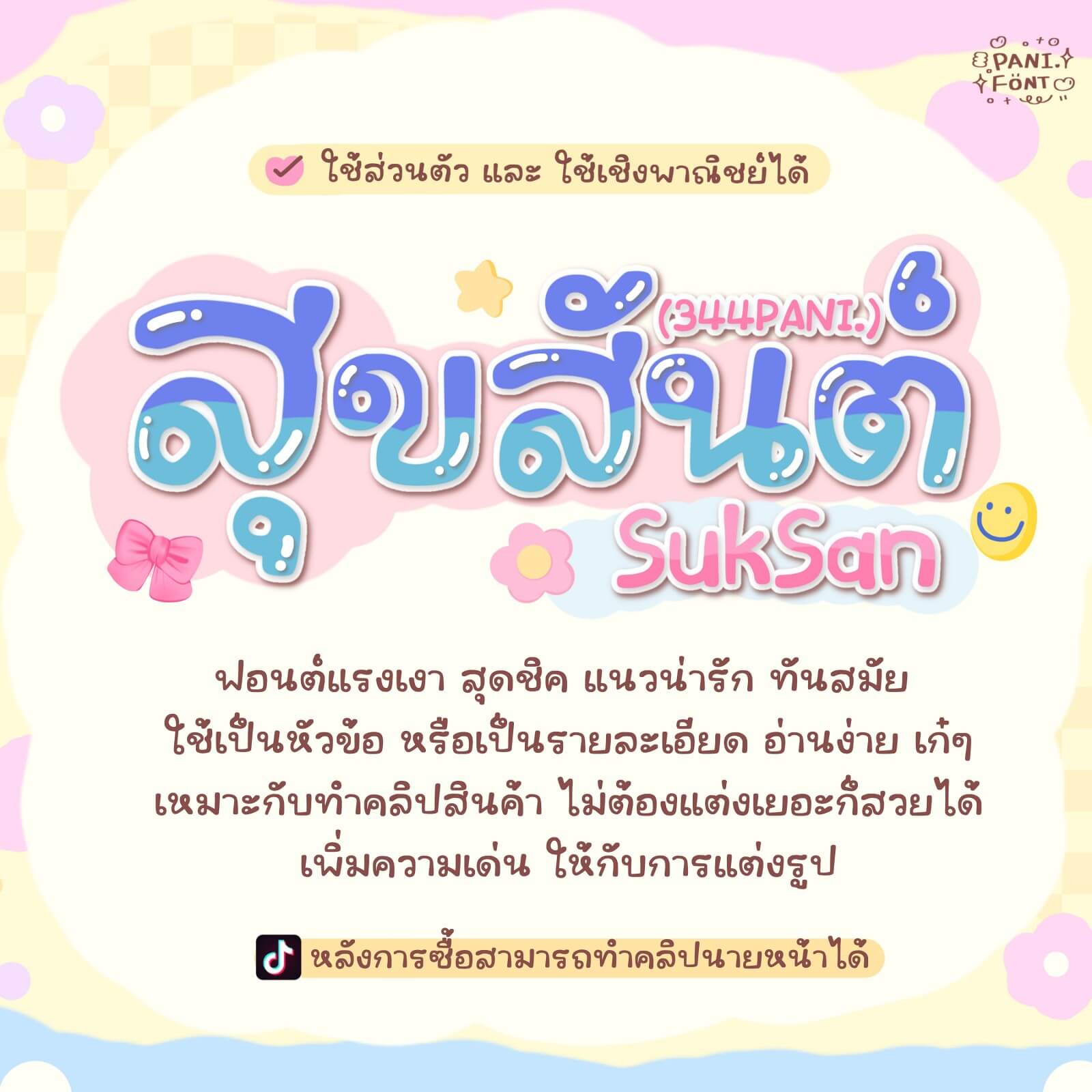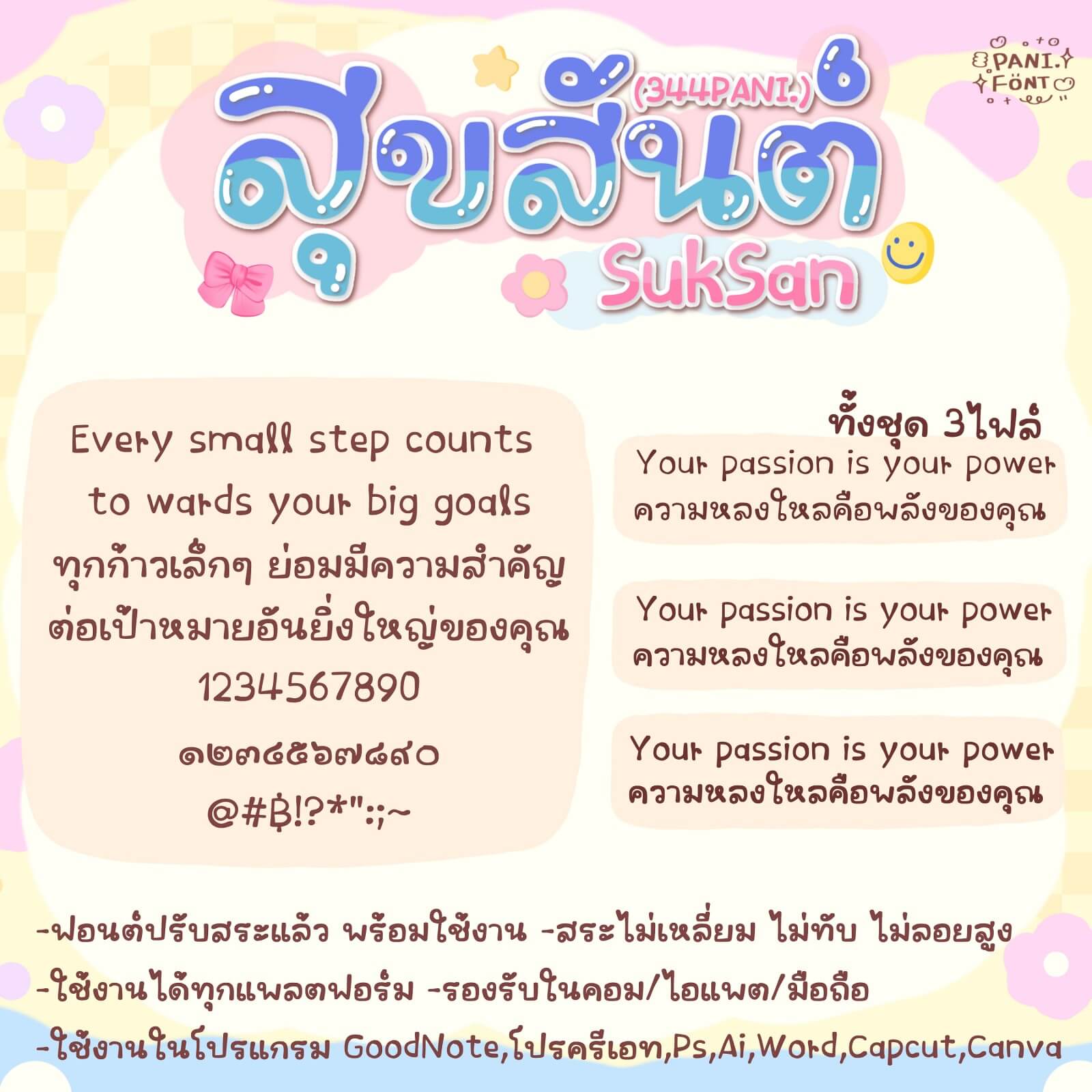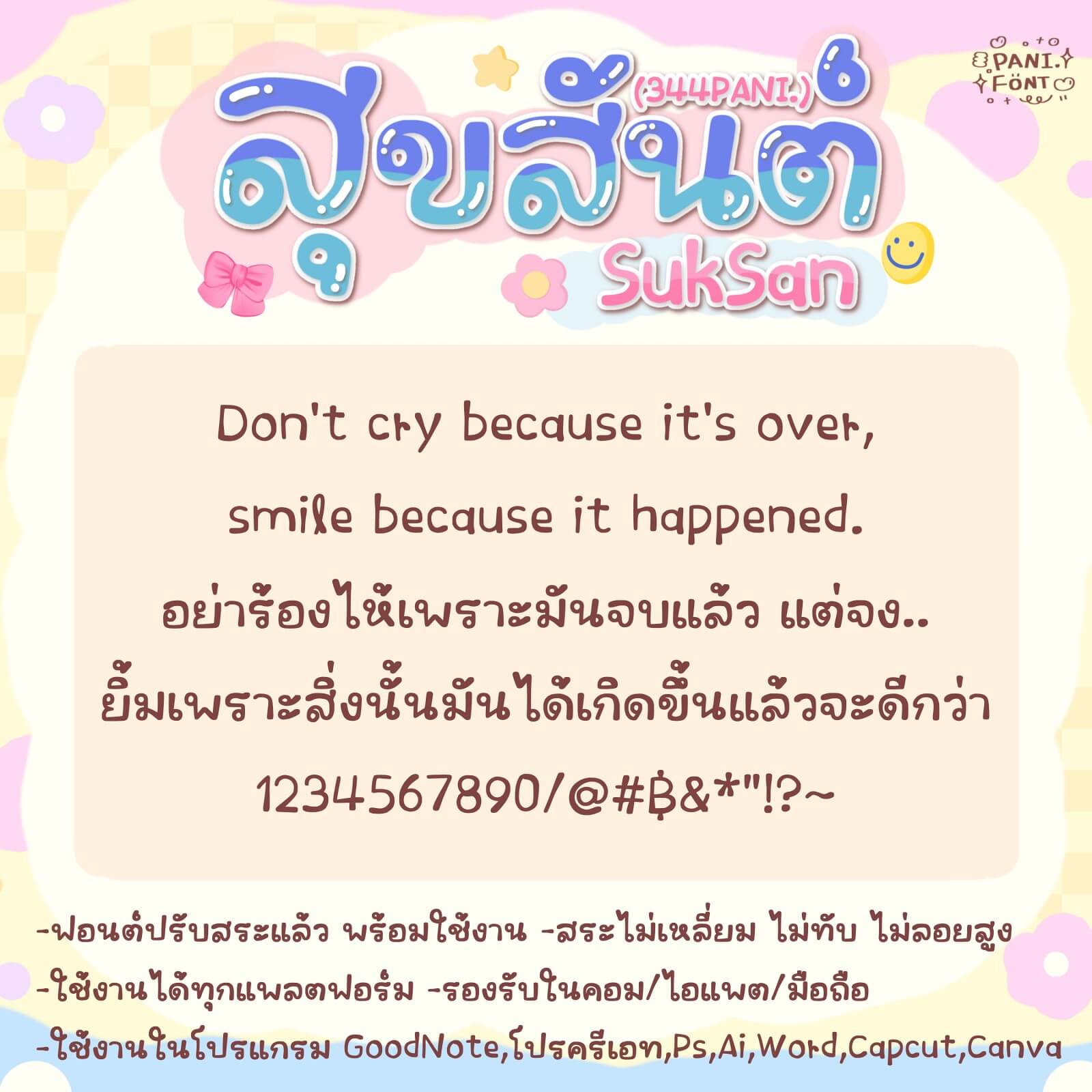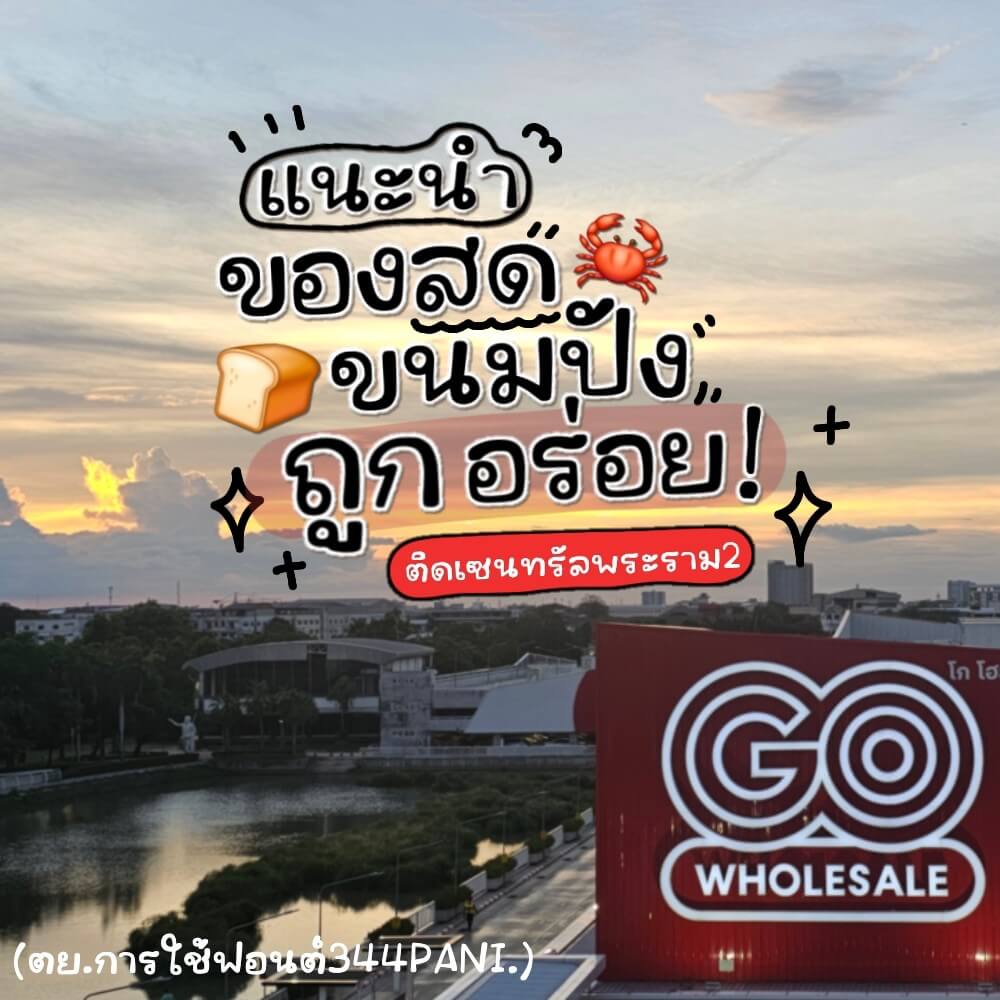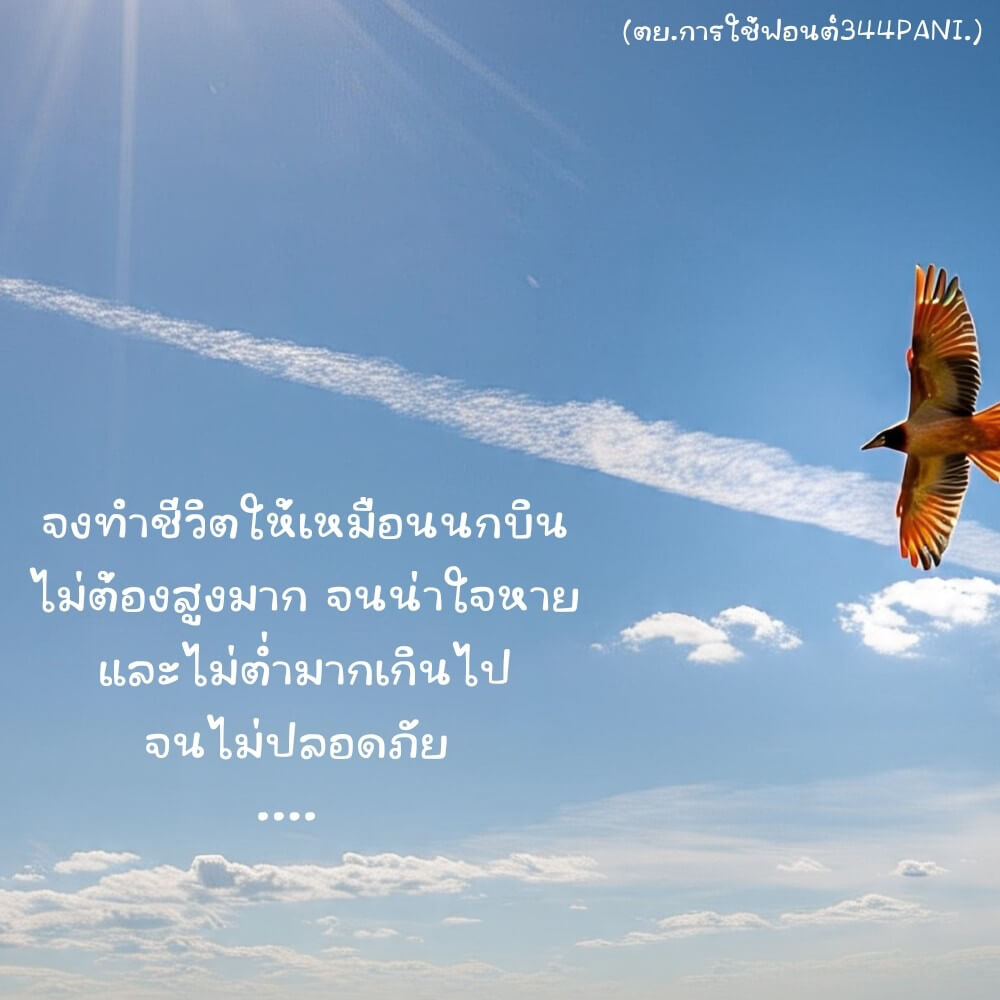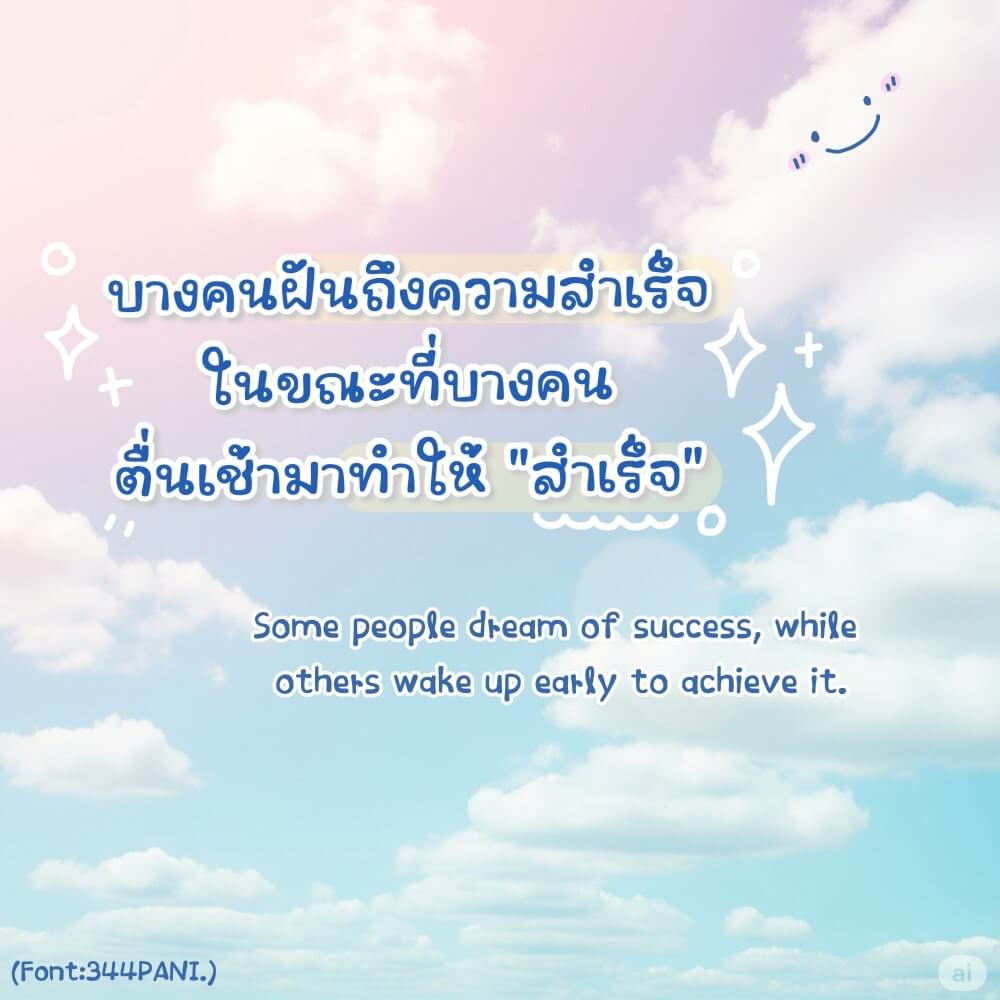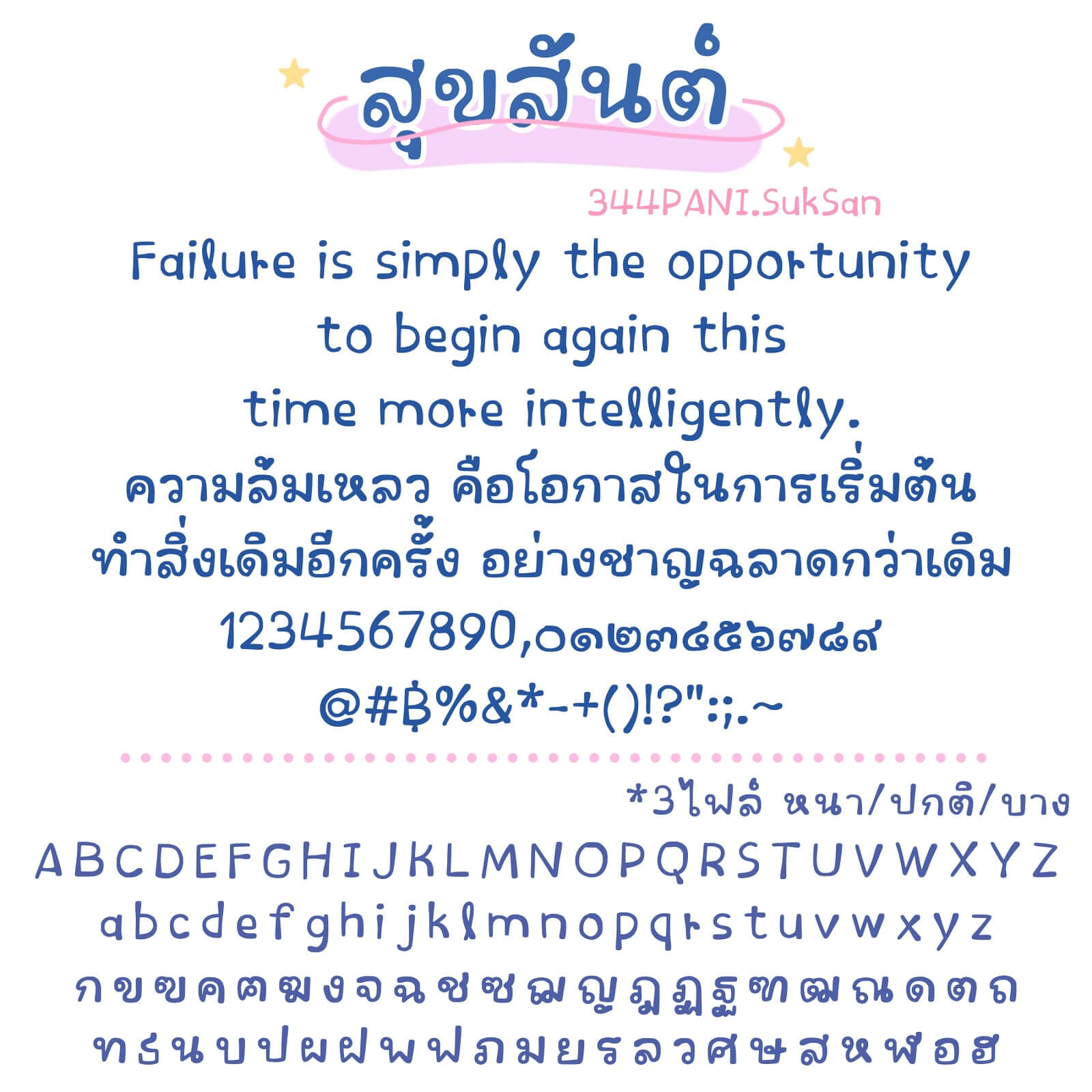
ฟอนต์ 344PANI.สุขสันต์ – ฟอนต์แรเงา สุดชิค แนวน่ารัก ทันสมัย ใช้เป็นหัวข้อ หรือเป็นรายละเอียด อ่านง่าย เก๋ๆ เหมาะกับทำคลิปสินค้า ไม่ต้องแต่งเยอะก็สวยได้ เพิ่มความเด่นให้กับการแต่งรูป
344PANI.สุขสันต์